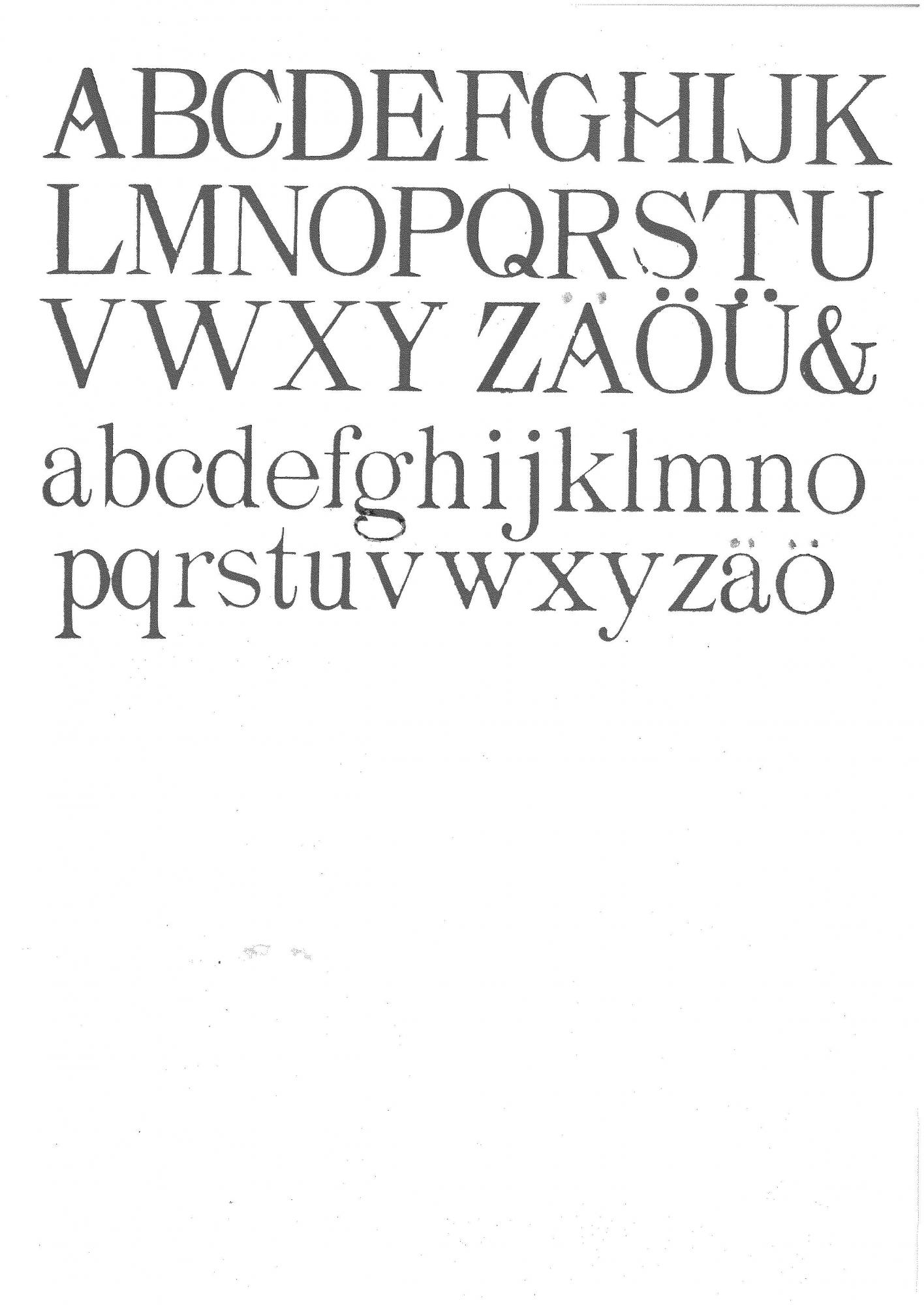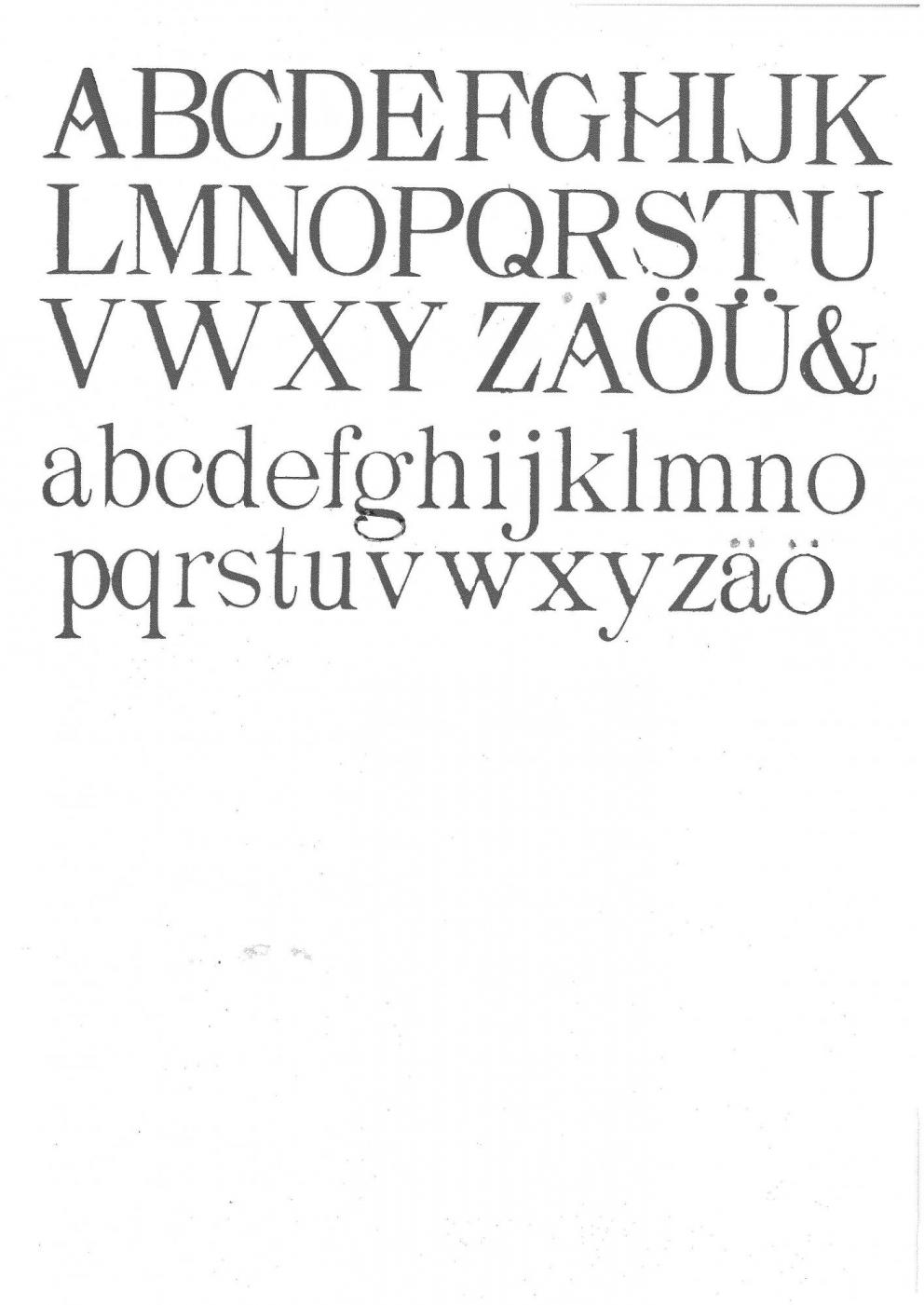
Identifikation von Messingschriften
Ich habe eine Schrift als Messingschrift zum prägen aus eine Betriebsauflösung erstanden. Leider konnte mir dort keiner sagen, welche Schrift es genau ist. Ich habe auch bei verschiedenen Online-Schrifterkennungsdiensten wie WhatTheFont oder WhatFontIs mein Glück versucht, war aber leider erfolglos. Danach bin ich auf dieses Forum gestoßen und hoffe, dass ihr mir weiterhelfen könnt.
Im Anhang findet ihr ein Schriftbeispiel mit möglichst vielen Buchstaben.
vor 8 Minuten schrieb Norbert P:
Die enthält ziemlich viele stilistische Elemente, die auch die Caxtonian (als Font: Gold Fever) vom Ende des 19. Jhs. (ca. 1880?) als einigermaßen "typisch viktorianische" Schrift aufweist.
Danke für deine schnelle Antwort. Du hast recht, es gibt da einige Gemeinsamkeiten, wie z.B. die charakteristischen Querstriche bei A und H. Leider weichen zu viele Buchstaben, wie das J oder das Q von meiner Schrift ab und die Relieflinie passt leider auch nicht.
Messingschriften waren eine ganz eigene Welt mit eigenen Namen und eigenen Entwürfen, die nicht von bekannten Schriftgestaltern stammten. Diese Schriften sind in unserer Grafikerwelt (Buchdruck/Fotosatz/Computersatz) kaum bekannt. Man müsste gezielt in Musterbüchern von Messingschriftanbietern suchen, welche aber auch selten sind.
Müsste ich die Schublade beschriften, ich würde sowas wie »viktorianische Antiqua« schreiben und dann wäre es gut.
Das ist allerdings sehr schade, dass es so schwer ist eine äquivalente graphische Schrift zu finden. Da wir auch Musterdrucke für die Prägungen anfertigen, wäre es schon gut, wenigstens eine sehr ähnliche Schrift auf dem PC zu haben.
Da ich hin und wieder mit alten Messing- und Bleischriften zu tun habe, suche ich des öfteren nach entsprechenden Fonts für den PC und bin nur in ganz vereinzelten Fällen nicht fündig geworden. Schade, ... naja vielleicht ergibt sich noch zufällig etwas.
diese Schrift hatte ich auch schon in die engere Wahl ähnlicher Schriftarten gezogen.
Ich versuche jedoch nach Möglichkeit eine Schrift zu finden, die vor allem den Querstrich, wie bei A und H sowie die ungewöhnliche Serifenform bei C oder J sowie eine möglichst passenden Q-Strich enthält.
Formal ähnlich wäre die